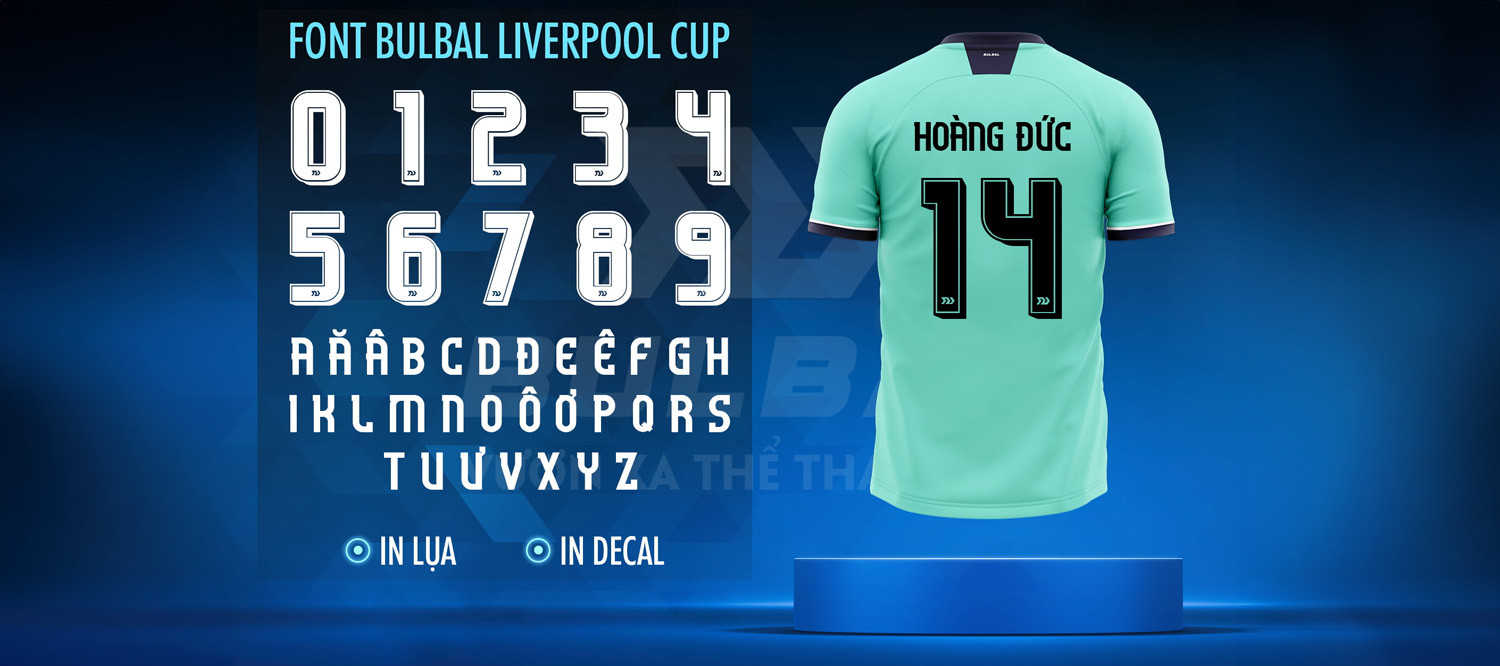
Font chữ áo thun là các kiểu chữ được thiết kế đặc biệt để sử dụng trên các sản phẩm áo thun. Những font chữ này thường mang phong cách trẻ trung, năng động và sáng tạo, giúp làm nổi bật các thiết kế và thu hút sự chú ý.
Font chữ là một phần không thể thiếu trong thiết kế áo thun, góp phần tạo nên sự độc đáo và thu hút cho sản phẩm. Việc lựa chọn font chữ phù hợp sẽ giúp thông điệp của bạn được truyền tải một cách hiệu quả và gây ấn tượng mạnh với người xem.
Các loại font chữ áo thun phổ biến
Font chữ đơn giản (sans-serif): Thường được sử dụng cho các thiết kế hiện đại, trẻ trung và dễ đọc.
Ví dụ: Helvetica, Arial, Roboto
Font chữ có chân (serif): Tạo cảm giác cổ điển, sang trọng và chuyên nghiệp.
Ví dụ: Times New Roman, Georgia, Garamond
Font chữ trang trí: Dùng để tạo điểm nhấn, phù hợp với các thiết kế độc đáo và cá tính.
Ví dụ: Script, Handwritten, Display
Font chữ 3D: Tạo hiệu ứng nổi bật, thu hút sự chú ý.
Độc Đáo và Sáng Tạo:
Font chữ áo thun thường có thiết kế độc đáo và sáng tạo, mang lại sự mới mẻ và phá cách cho các sản phẩm áo thun.
Chúng có thể mang nhiều phong cách khác nhau, từ hiện đại, cổ điển đến vui nhộn và nghệ thuật.
Dễ Đọc:
Mặc dù có thiết kế sáng tạo, font chữ áo thun vẫn cần đảm bảo tính dễ đọc, đặc biệt khi nhìn từ xa hoặc trên nền vải màu sắc.
Các ký tự thường rõ ràng và sắc nét, giúp truyền tải thông điệp một cách hiệu quả.
Tương Phản Tốt:
Font chữ áo thun thường có độ tương phản cao để dễ dàng nhìn thấy trên các nền vải có màu sắc đa dạng.
Độ tương phản giúp chữ nổi bật hơn và thu hút sự chú ý.
Đa Dạng Phong Cách:
Có rất nhiều phong cách font chữ áo thun để lựa chọn, từ thanh lịch, đơn giản đến phức tạp và cầu kỳ.
Sự đa dạng này giúp các nhà thiết kế dễ dàng lựa chọn font chữ phù hợp với thông điệp và phong cách của từng mẫu áo thun.
Cách chọn font chữ áo thun phù hợp
Phong cách thiết kế: Chọn font chữ phù hợp với phong cách chung của thiết kế.
Thông điệp muốn truyền tải: Font chữ có thể giúp nhấn mạnh ý nghĩa của thông điệp.
Đối tượng khách hàng: Lựa chọn font chữ phù hợp với sở thích và độ tuổi của khách hàng.
Kích thước và không gian: Cân nhắc kích thước và không gian in ấn để chọn font chữ phù hợp.
Thiết Kế Áo Thun Thời Trang:
Font chữ áo thun được sử dụng rộng rãi trong ngành thời trang để thiết kế các mẫu áo thun độc đáo và phong cách.
Chúng giúp tạo nên các sản phẩm áo thun mang dấu ấn riêng và thu hút sự quan tâm của khách hàng.
Áo Thun Sự Kiện:
Các sự kiện như lễ hội, hội thảo, cuộc thi thể thao thường sử dụng áo thun có in chữ để quảng bá và ghi dấu ấn.
Font chữ áo thun giúp truyền tải thông điệp của sự kiện một cách rõ ràng và ấn tượng.
Áo Thun Thương Hiệu:
Nhiều công ty và thương hiệu sử dụng áo thun như một phương tiện quảng cáo hiệu quả.
Font chữ áo thun giúp làm nổi bật logo và thông điệp của thương hiệu, tạo ấn tượng mạnh mẽ với người nhìn.
Áo Thun Cá Nhân Hóa:
Áo thun cá nhân hóa là xu hướng phổ biến, cho phép người dùng thiết kế áo thun theo ý thích riêng.
Font chữ áo thun giúp tạo nên các sản phẩm áo thun độc đáo và mang đậm dấu ấn cá nhân.
Font chữ áo thun đóng vai trò quan trọng trong việc tạo nên các thiết kế áo thun độc đáo và ấn tượng. Với các đặc điểm như tính sáng tạo, dễ đọc và đa dạng phong cách, font chữ áo thun giúp truyền tải thông điệp một cách hiệu quả và thu hút sự chú ý của người nhìn. Việc lựa chọn font chữ phù hợp sẽ giúp các sản phẩm áo thun trở nên nổi bật và mang dấu ấn riêng, góp phần quan trọng trong thành công của các thiết kế thời trang.